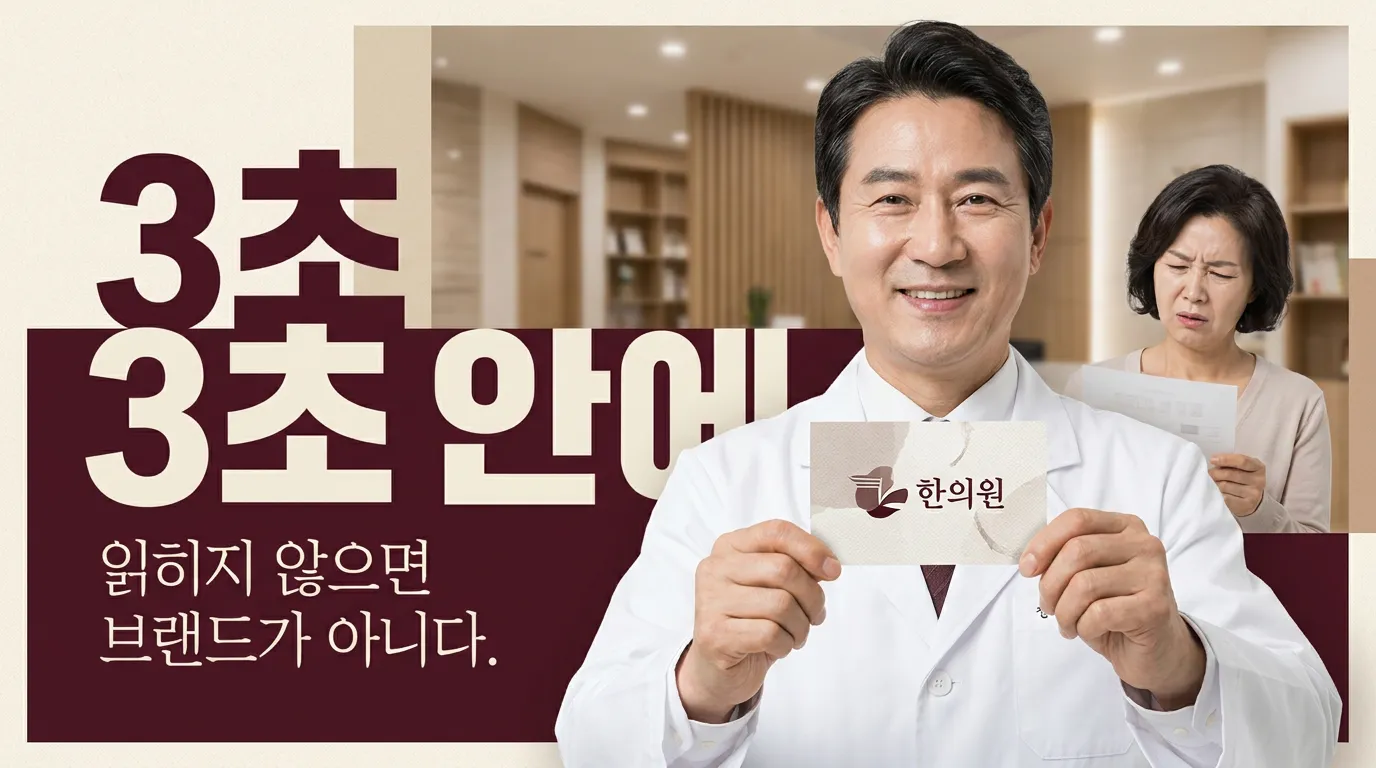
한의원 로고 폰트, 한글이냐 한자냐보다 먼저 봐야 할 3초 기준
한의원 로고 폰트에서 한글·한자 선택이 환자 신뢰도에 주는 차이와 실제 적용 기준을 원장님 눈높이로 정리했습니다.
시안에 한자가 들어가는 순간, 원장님은 ‘전문적으로 보인다’고 느끼지만 환자는 ‘읽어야 하나?’부터 생각합니다.
한자가 들어가면 더 믿어 보일까요?
한자는 분명 힘이 있습니다. 오래된 의학, 처방, 깊이 같은 이미지를 빠르게 가져오죠. 특히 ‘수’, ‘본’, ‘청’, ‘담’처럼 의미가 단단한 글자는 심볼처럼 쓰기 좋습니다.
그런데 로고의 첫 임무는 해석이 아니라 식별입니다. 지나가던 환자가 3초 안에 이름을 읽지 못하면, 멋은 남아도 기억은 흐려집니다. 그래서 저는 한자를 메인 이름으로 크게 쓰는 방식은 조심합니다.
이렇게 하세요. 한의원 이름은 한글로 또렷하게 두고, 한자는 심볼·낙관·보조 표기로 낮춰 쓰면 됩니다. 한자는 ‘읽는 글자’보다 ‘분위기를 잡는 장치’로 쓸 때 덜 낡아 보입니다.
그럼 한글 로고가 무조건 낫나요?
아닙니다. 한글도 어떻게 쓰느냐가 더 큽니다. 너무 둥근 손글씨는 편안하지만 진료의 밀도가 약해 보일 수 있고, 너무 각진 고딕은 깔끔하지만 한의원의 온기가 빠질 수 있습니다.
보건복지부의 2024년 한방의료이용 실태조사를 보면 한방의료 이용 경험은 50대 79.8%, 60세 이상 86.6%로 높지만, 30대도 47.8%, 40대도 66.1%입니다. 환자는 이미 여러 세대가 섞여 있습니다. ‘어르신이 좋아할 한자’ 하나로만 잡기엔 넓어진 시장이에요. (mohw.go.kr)
이렇게 하세요. 한글 메인 로고는 명조 계열의 단정함이나, 획 대비가 약한 세리프형 한글을 먼저 검토하세요. 붓글씨는 정말 자신 있을 때만 씁니다. 붓의 힘보다 획의 정리가 먼저입니다.
환자는 글씨체에서 무엇을 먼저 보나요?
환자는 폰트 이름을 모릅니다. 대신 ‘여기 오래 갈 곳인가’, ‘너무 상업적이지 않나’, ‘설명을 잘해줄 것 같나’를 봅니다. 한방의료 선택 이유도 ‘치료효과가 좋아서’가 42.5%로 가장 높고, ‘질환에 맞는 진료’가 뒤따릅니다. 결국 로고도 효과와 진료의 태도를 방해하지 않아야 합니다. (mohw.go.kr)
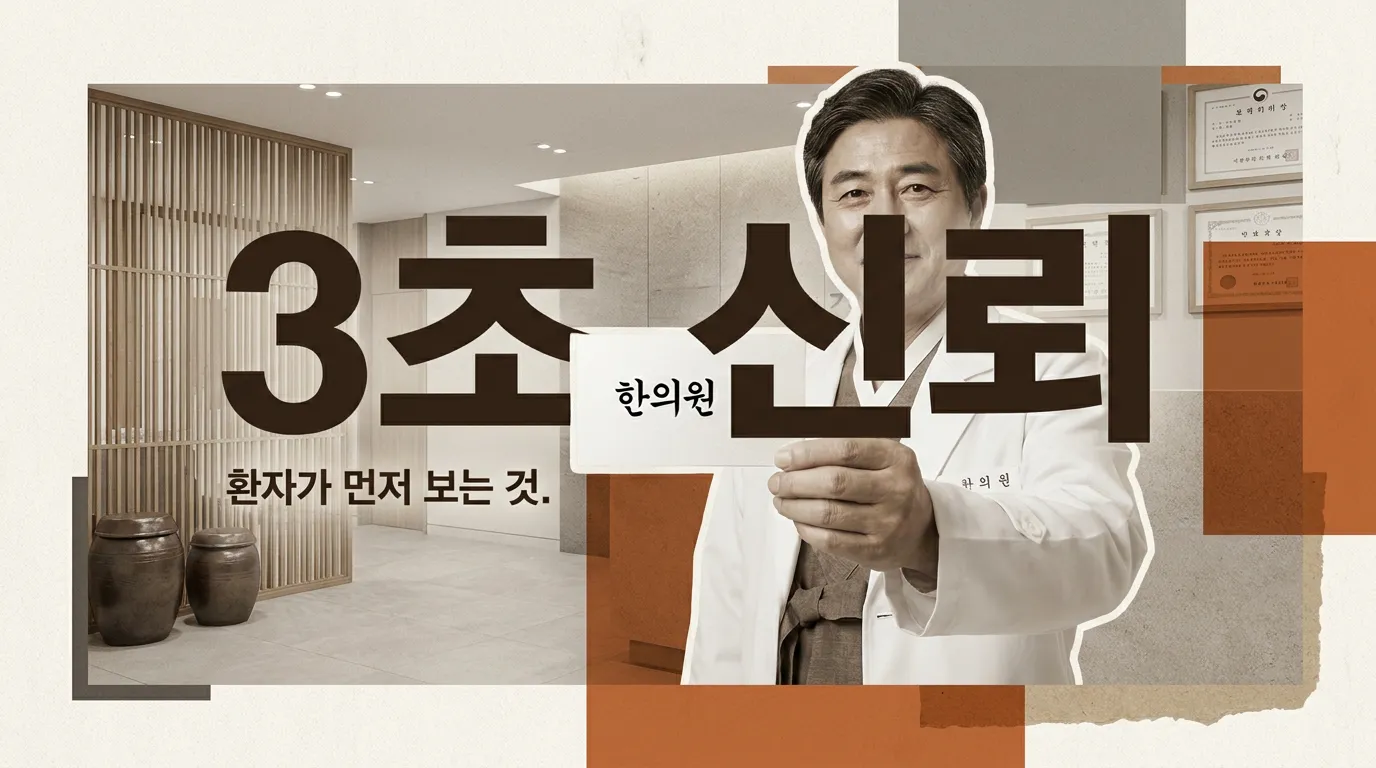
이렇게 하세요. 획이 너무 가늘면 약해 보이고, 너무 두꺼우면 프랜차이즈처럼 보입니다. 한의원 로고 폰트는 중간 굵기에서 자간을 조금 넓히는 쪽이 안전합니다. 여백이 생기면 조용해지고, 조용하면 진료 공간에 더 잘 붙습니다.
한글과 한자를 같이 쓰려면 어디까지가 좋을까요?
같이 쓰는 건 좋습니다. 다만 둘이 같은 크기로 싸우면 안 됩니다. 한글은 이름을 맡고, 한자는 세계관을 맡아야 합니다. 예를 들어 ‘○○한의원’은 한글로 읽히게 두고, 뜻이 좋은 한 글자만 도장처럼 쓰는 식입니다.
제가 마크에서 한의원 로고를 볼 때도 먼저 묻는 건 ‘한자를 넣을까요?’가 아닙니다. ‘환자가 이 이름을 한 번에 부를 수 있나요?’입니다. 부르기 쉬운 이름 위에 의미가 얹혀야 오래 갑니다.
이렇게 하세요. 개원 전이라면 로고를 A4에 작게 뽑아 보세요. 5미터 뒤에서 한글 이름이 먼저 읽히면 통과. 한자가 먼저 보이면 조정. 모바일 예약 화면에서 뭉개지면 다시 조정. 작품 둘러보기 전에 원장님 로고도 이 기준으로 먼저 확인하면 됩니다.
지금 당장 할 행동 한 줄: 한글 이름을 메인으로 두고, 한자는 ‘읽히는 글자’가 아니라 ‘기억되는 심볼’로 한 단계 낮춰 보세요.